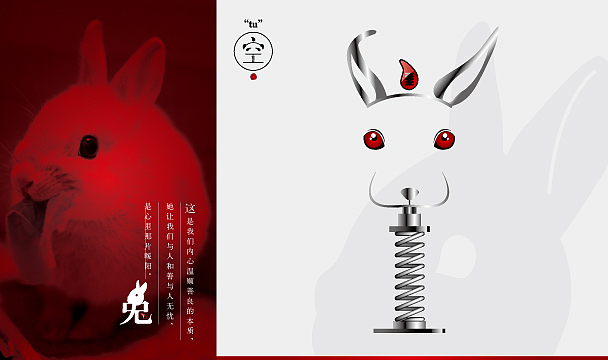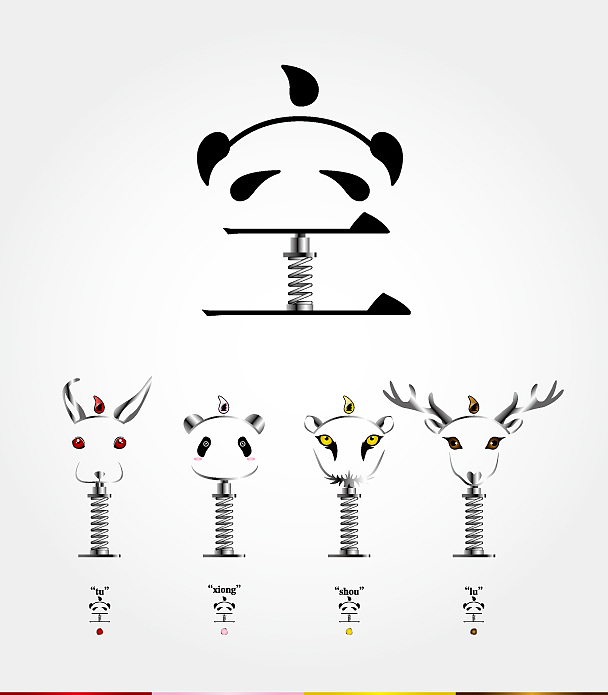
由字体设计引发的个人对人性浅薄的认识(空)
其实,本来这只是个作业的命题之一:空!
我想了想,觉得这个字好难做,因为它实在太广义了。广义到我觉得从某种层面我无法定义它。何为空?也许我们本就是不存在的,我们本就是空的,而人性填充在里面,所以我们有各种各样的想法与行为,这却始于我们或温婉善良或高贵向往或贪婪欲望或胆怯谨慎……等等!最后,这本来不复杂的一件事变成了一种我对空很狭义很浅薄的认识!
其实撇开那些自我的心理活动与想法,我个人还挺喜欢这些个家伙!想着空了再改改完善下做成十二生肖,一整套!
这可能算不上是真正的字体设计,但却是我想法的衍伸!